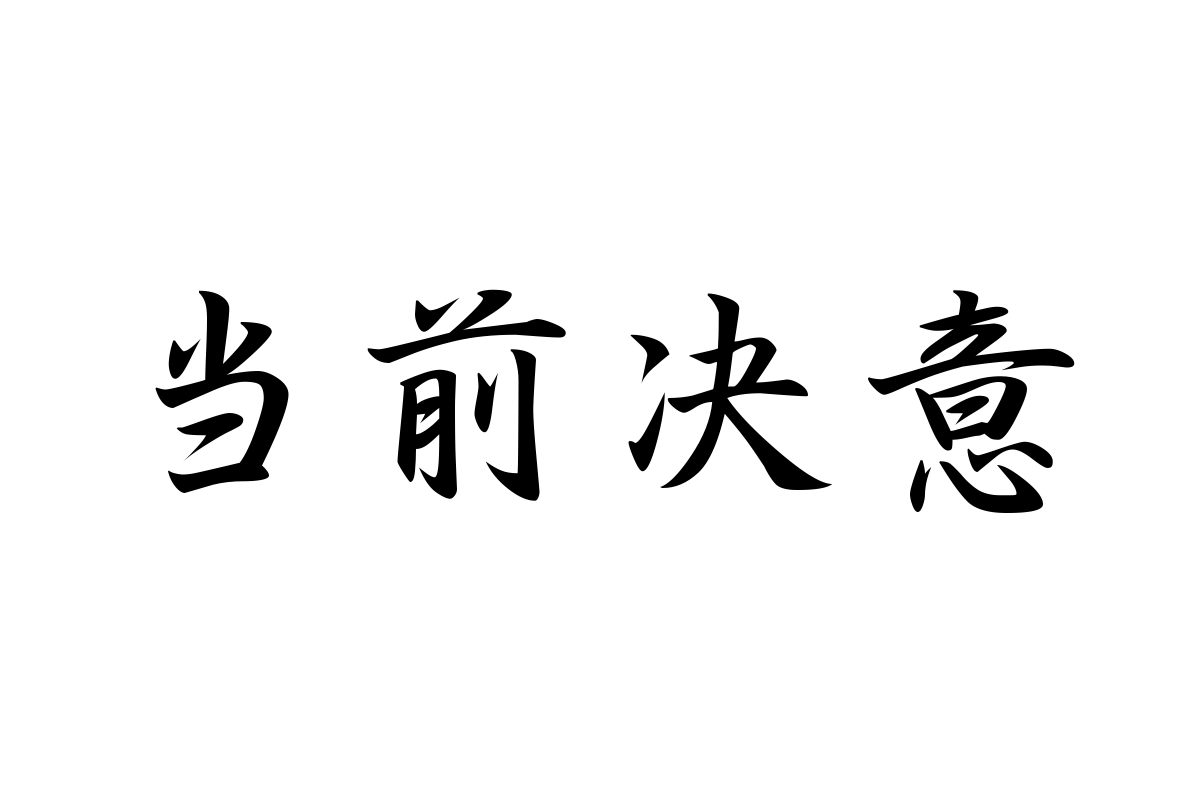
三极行书简体是一款中文字体,由三极公司设计。这款字体以其独特的风格和艺术感而闻名,适用于各种需要展示个性和创意的场合。
三极行书简体的特点在于其流畅、灵动的笔画,以及丰富的字形变化。这种字体适合用于标题、标志、广告、书籍封面等需要突出个性和创意的场合。它的设计灵感来源于传统的行书,但又融入了现代审美元素,使得整体风格既古典又时尚。
三极行书简体在细节上也非常精致,无论是笔画的粗细、间距还是结构,都经过精心设计,以确保阅读的舒适性和美观性。同时,该字体还支持多种字重和样式,可以满足不同场景的需求。
总的来说,三极行书简体是一款非常优秀的中文字体,适合用于需要展示个性和创意的场合。
三极行书简体